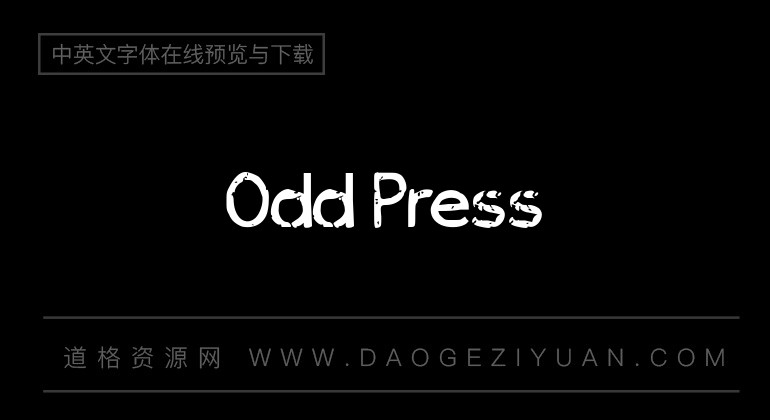
Odd Press
Odd Press 是一款由丹麦设计师 Kristian Hammerstad 设计的字体。它是一款手写风格的字体,有着独特的外观,可以让您的文字充满活力。它具有轻松、活泼、可爱的外观,可以用于各种印刷品、网页和平面设计等。它的字符设计独特,具有轻松的表现力,可以让您的文字显得更加生动有趣。
Odd Press是一款非常不错的手写艺术字体,具有很好的视觉感,适合于文化类的宣传设计、商业类品牌的广告和产品包装设计以及个性化文字排版等较多场景。